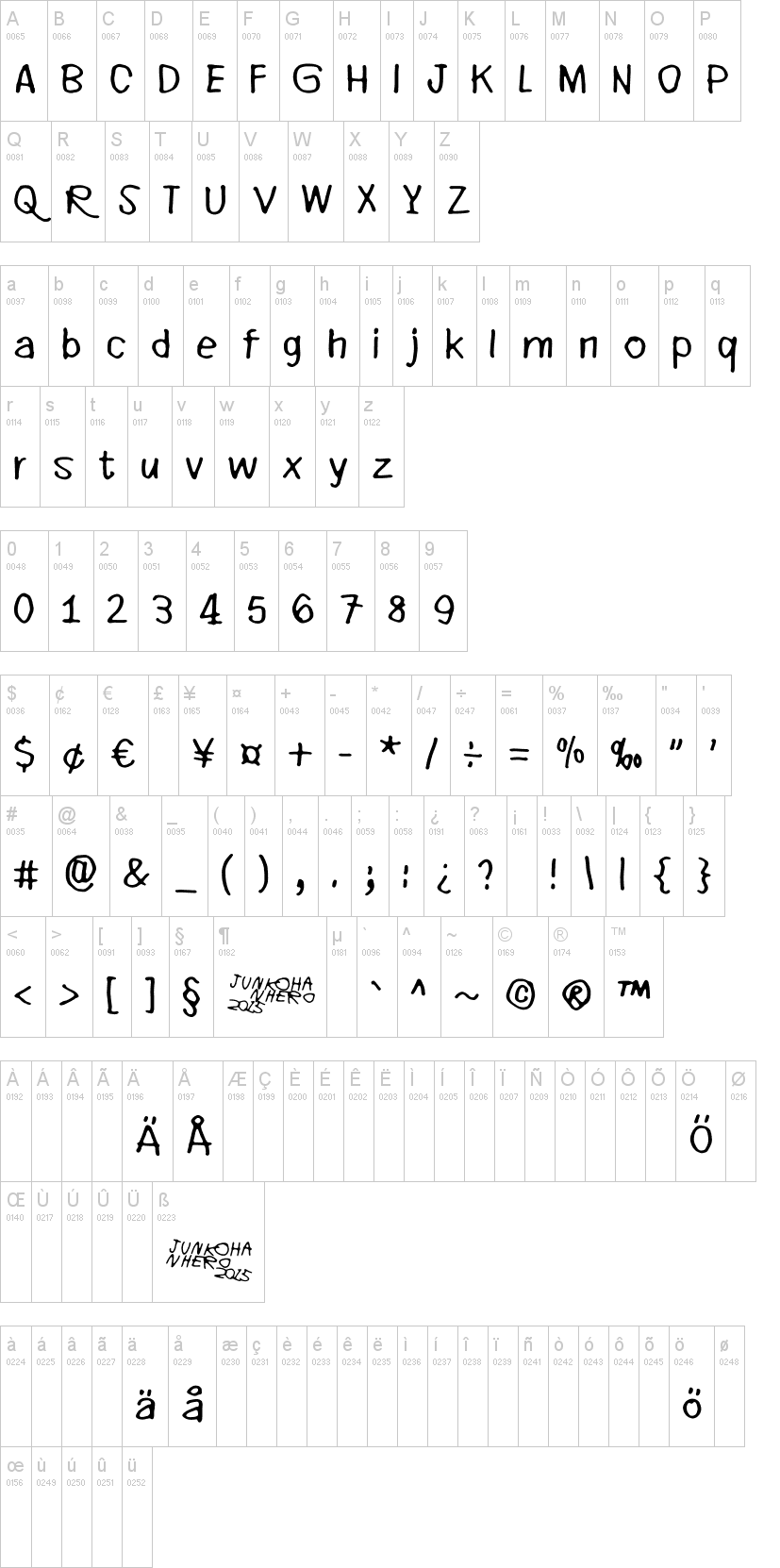
Every little thing that you do
Every little thing that you do是一款非常不错的手写艺术字体,具有很好的视觉感,适合于文化类的宣传设计、商业类品牌的广告和产品包装设计以及个性化文字排版等较多场景。
Every little thing that you do字符映射图